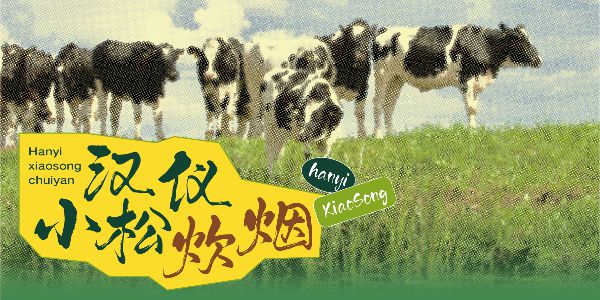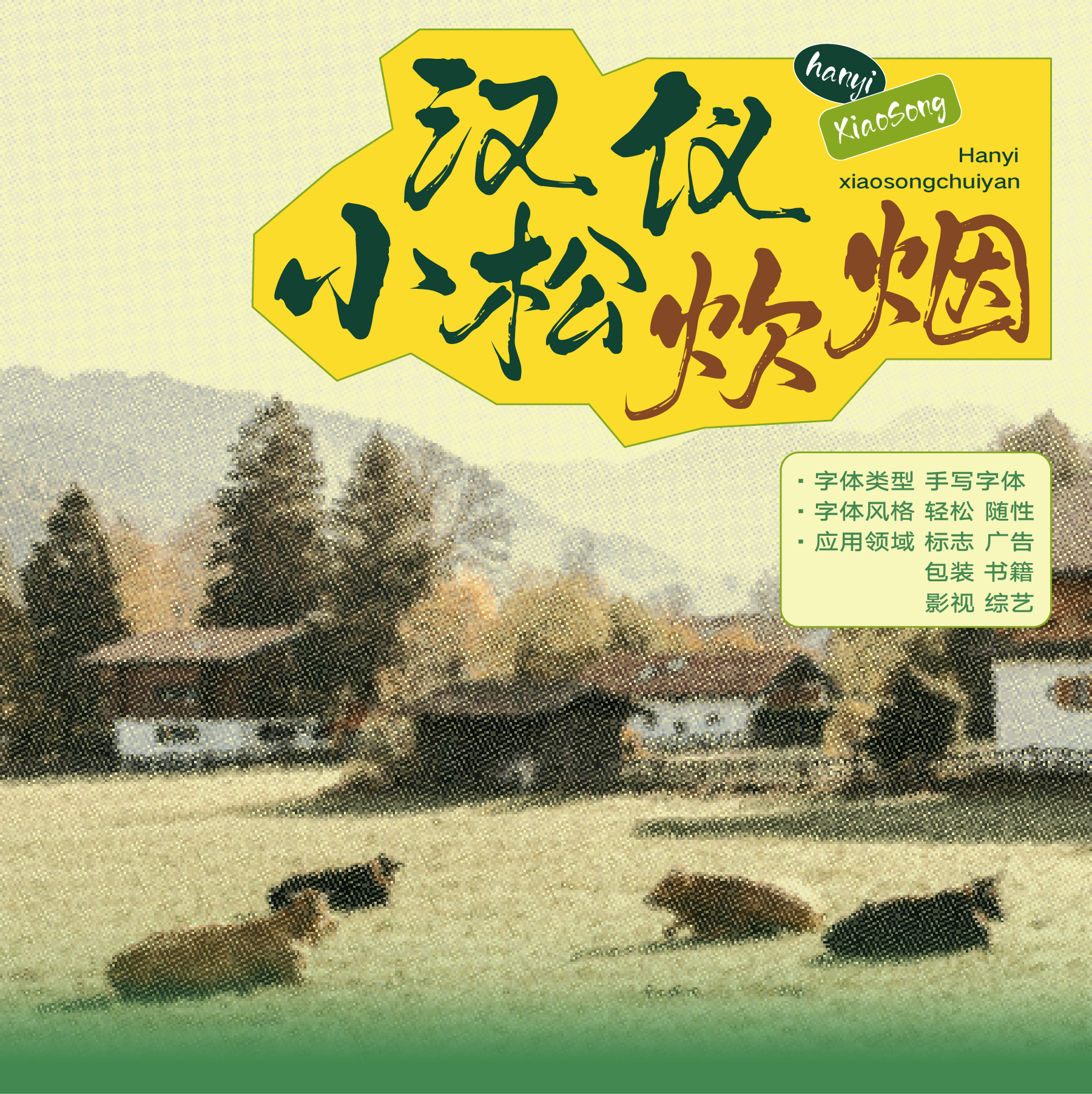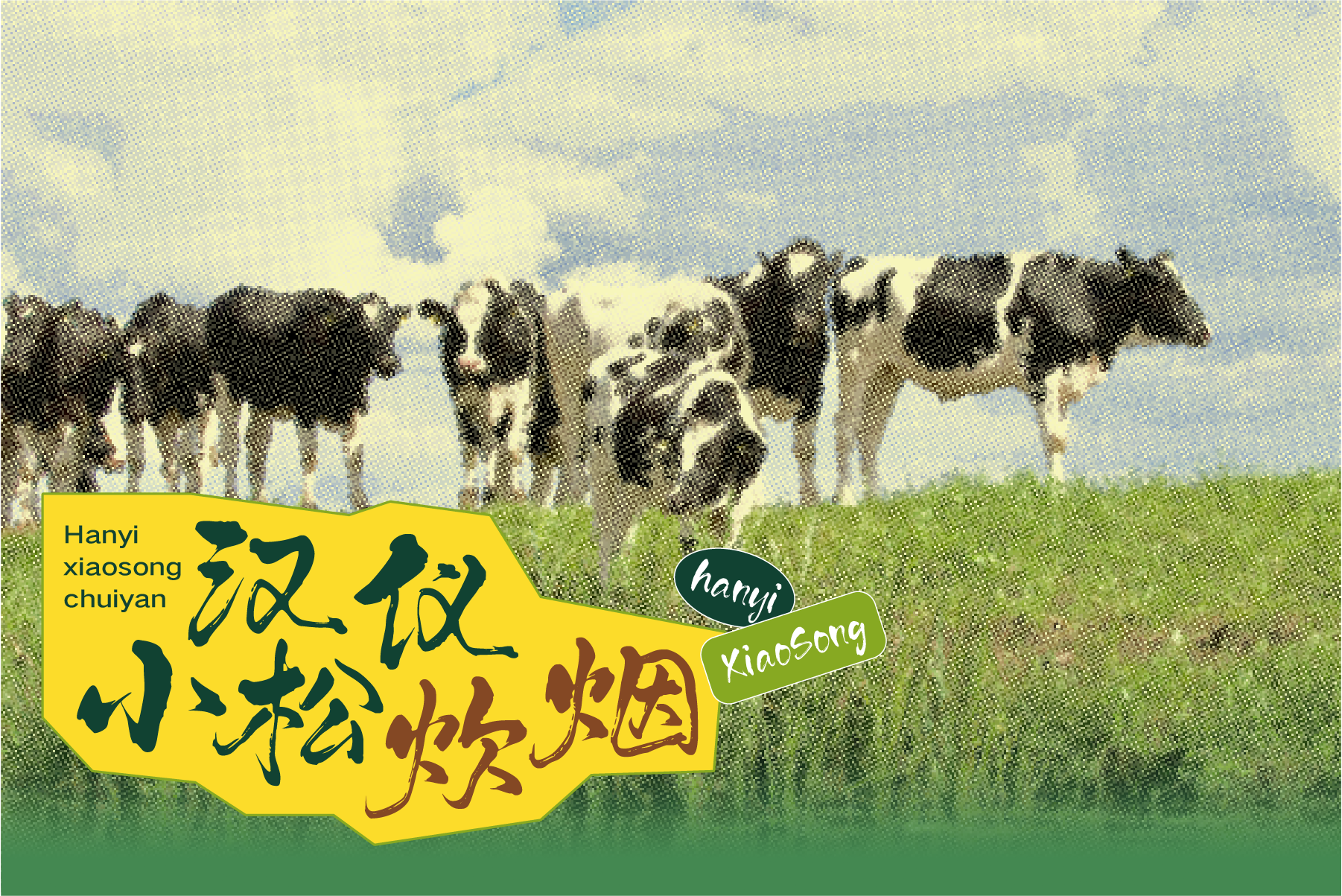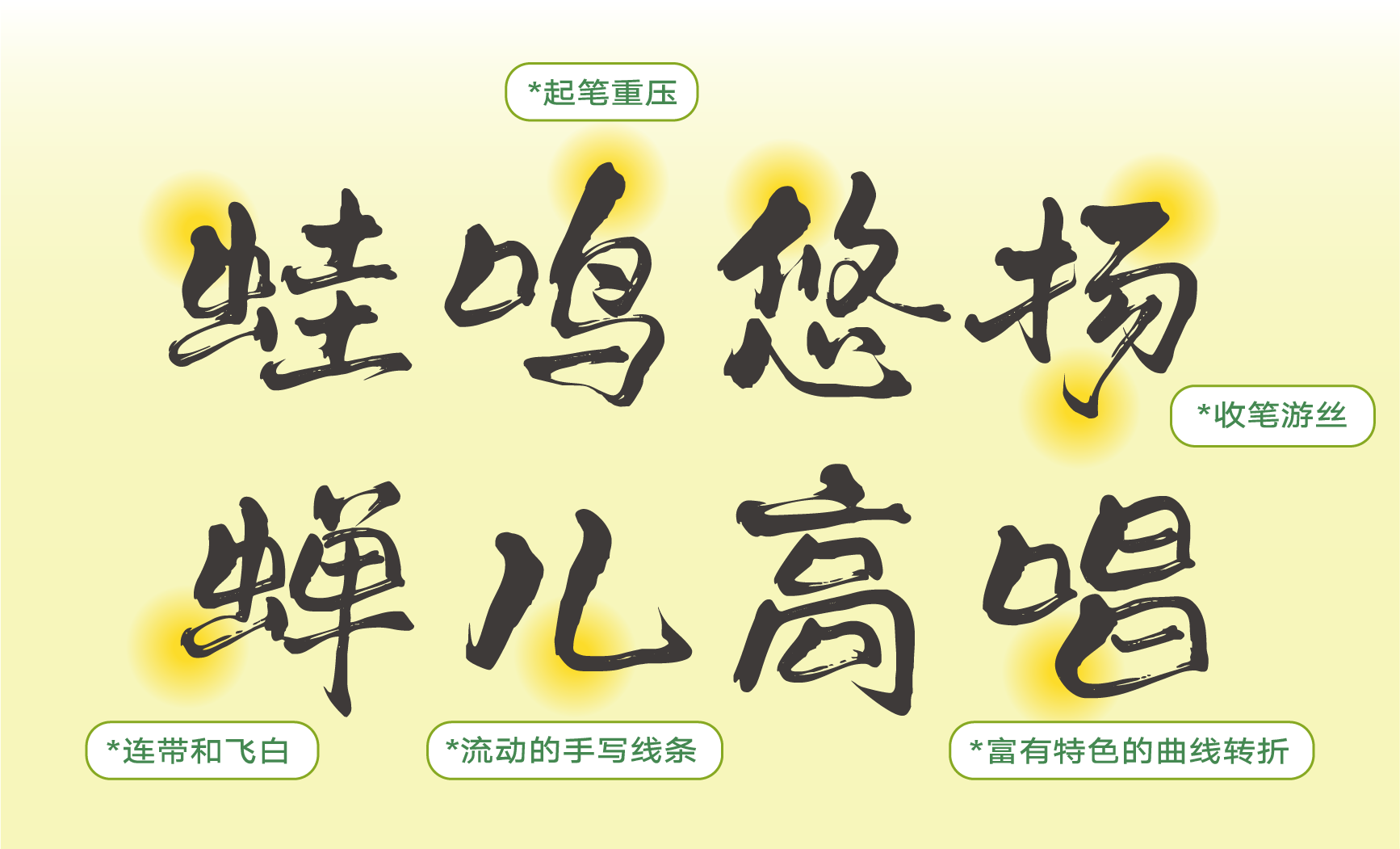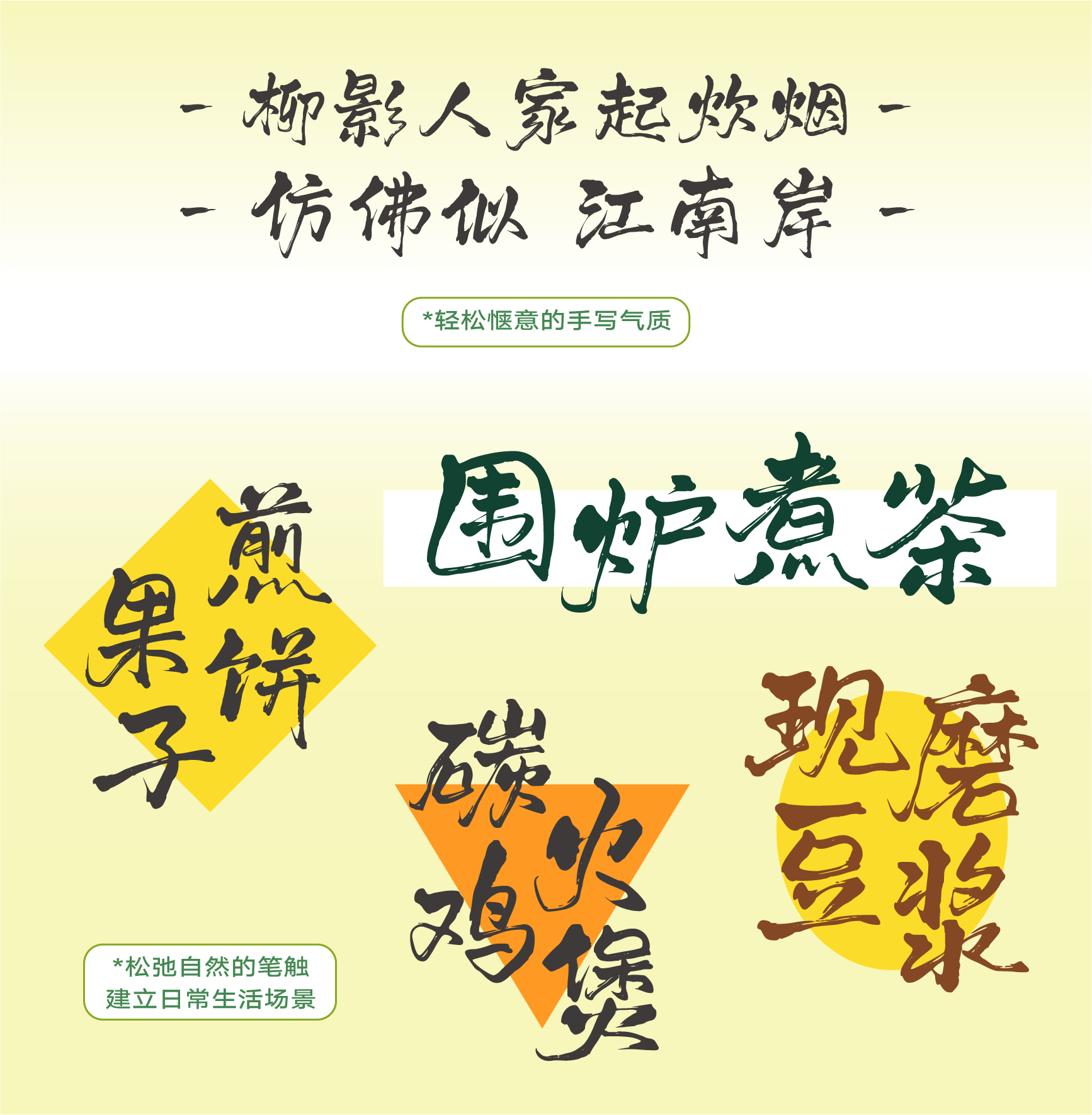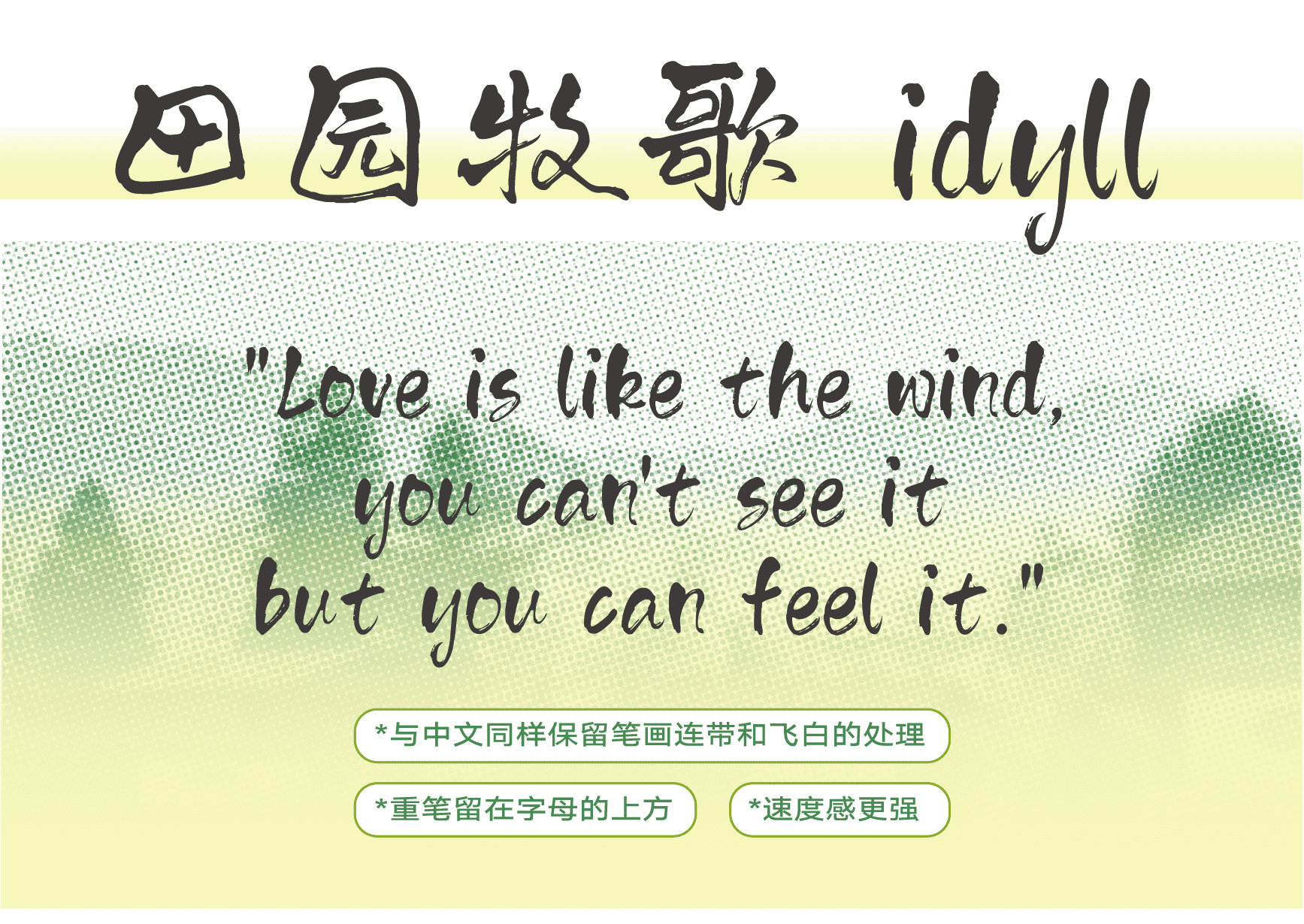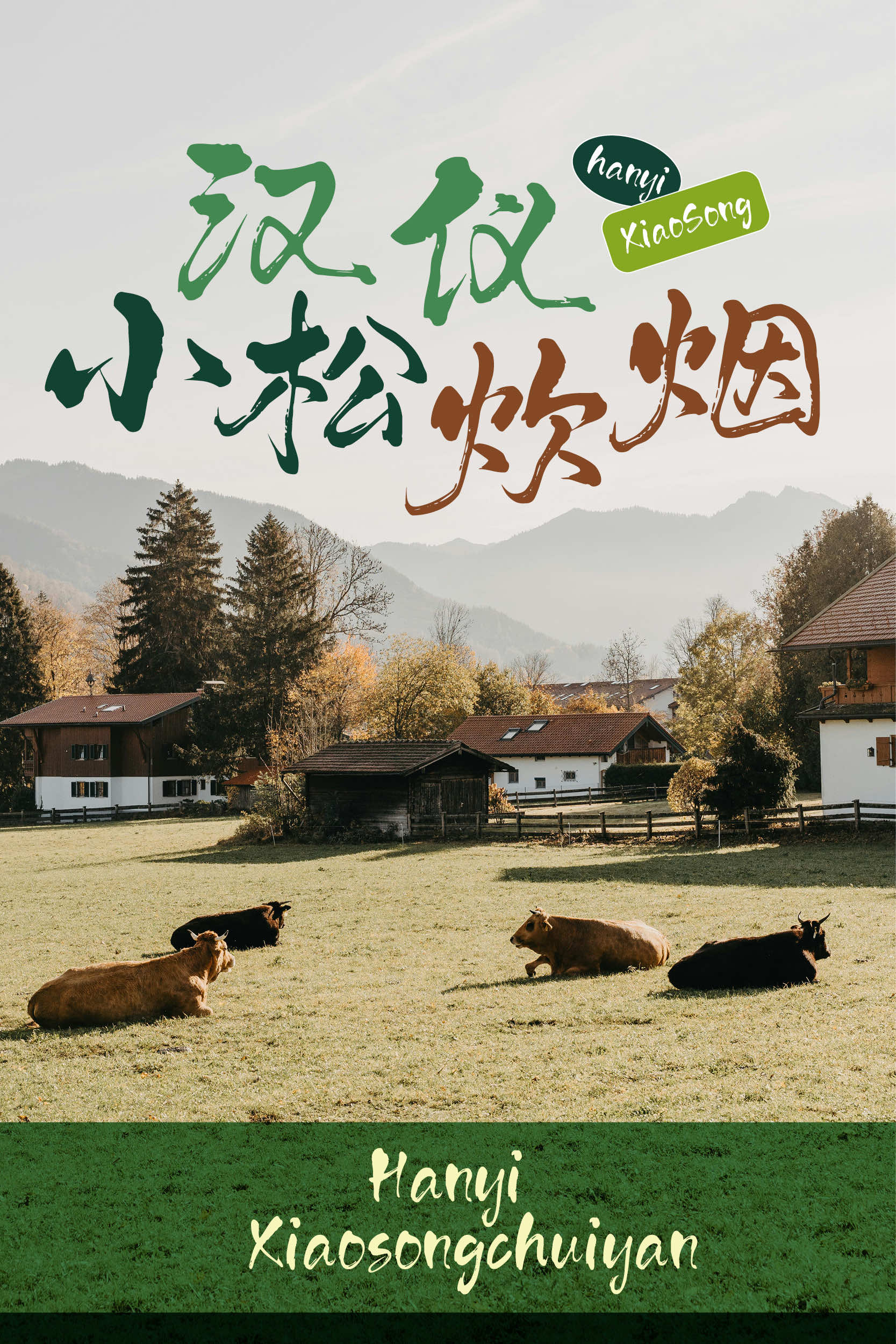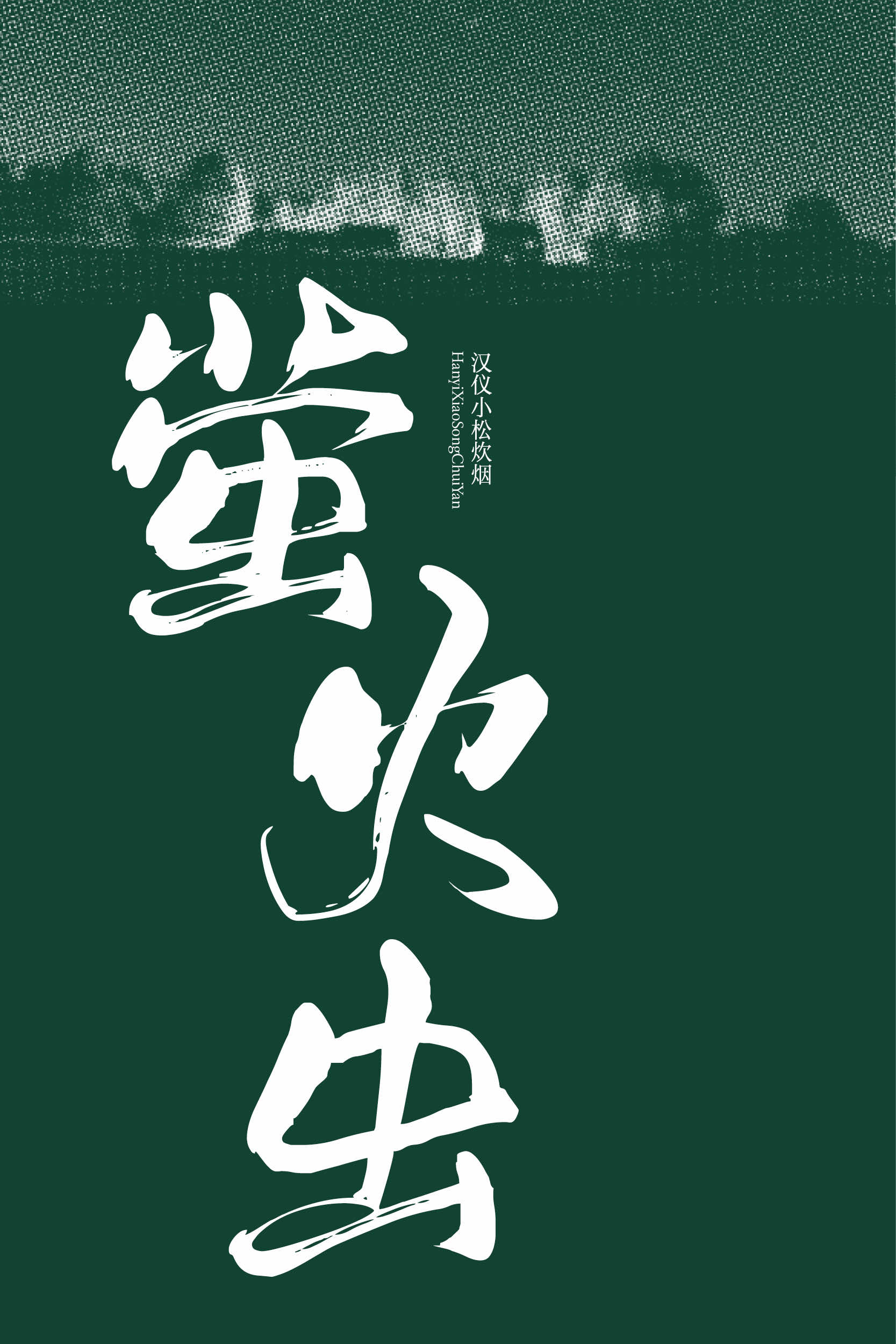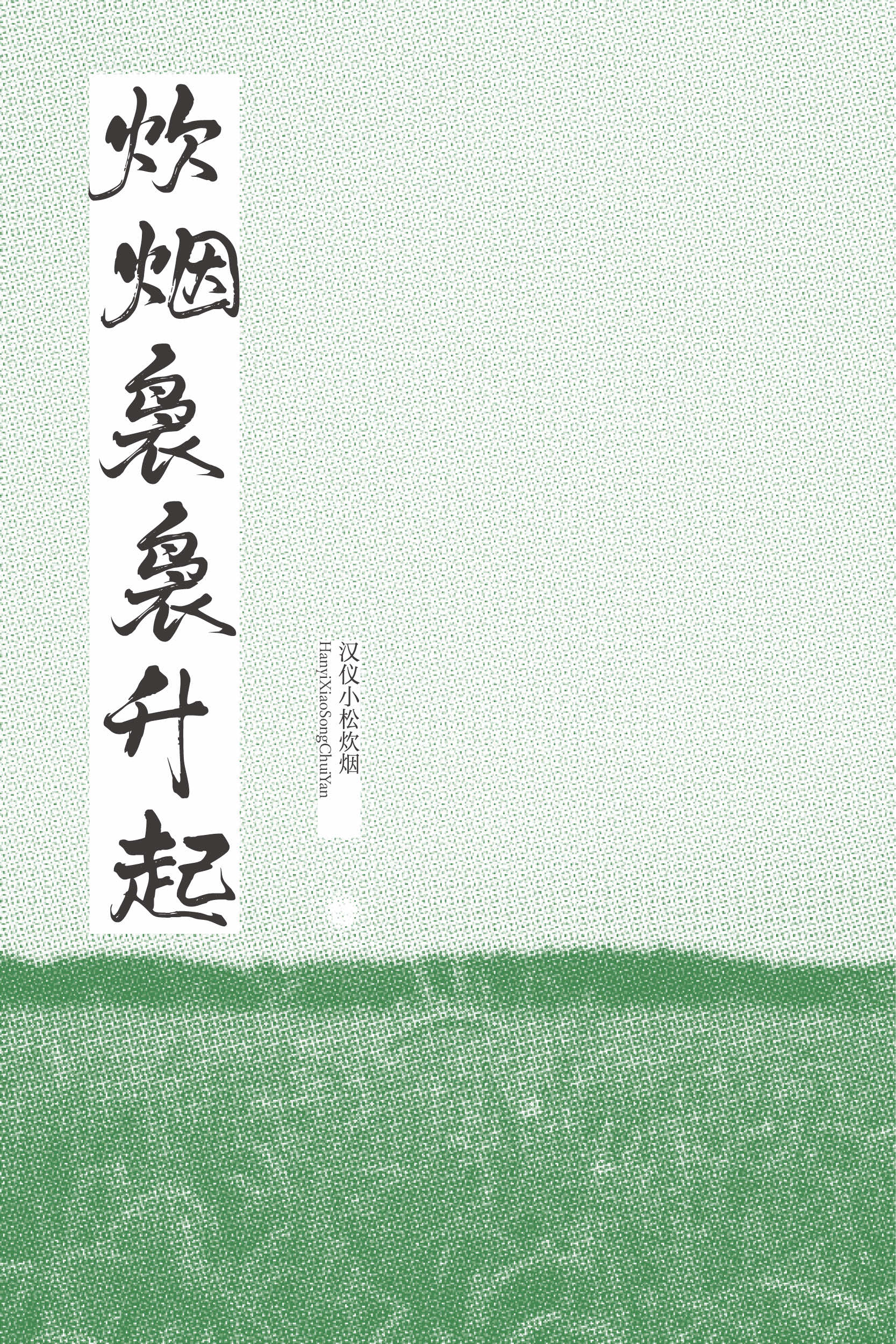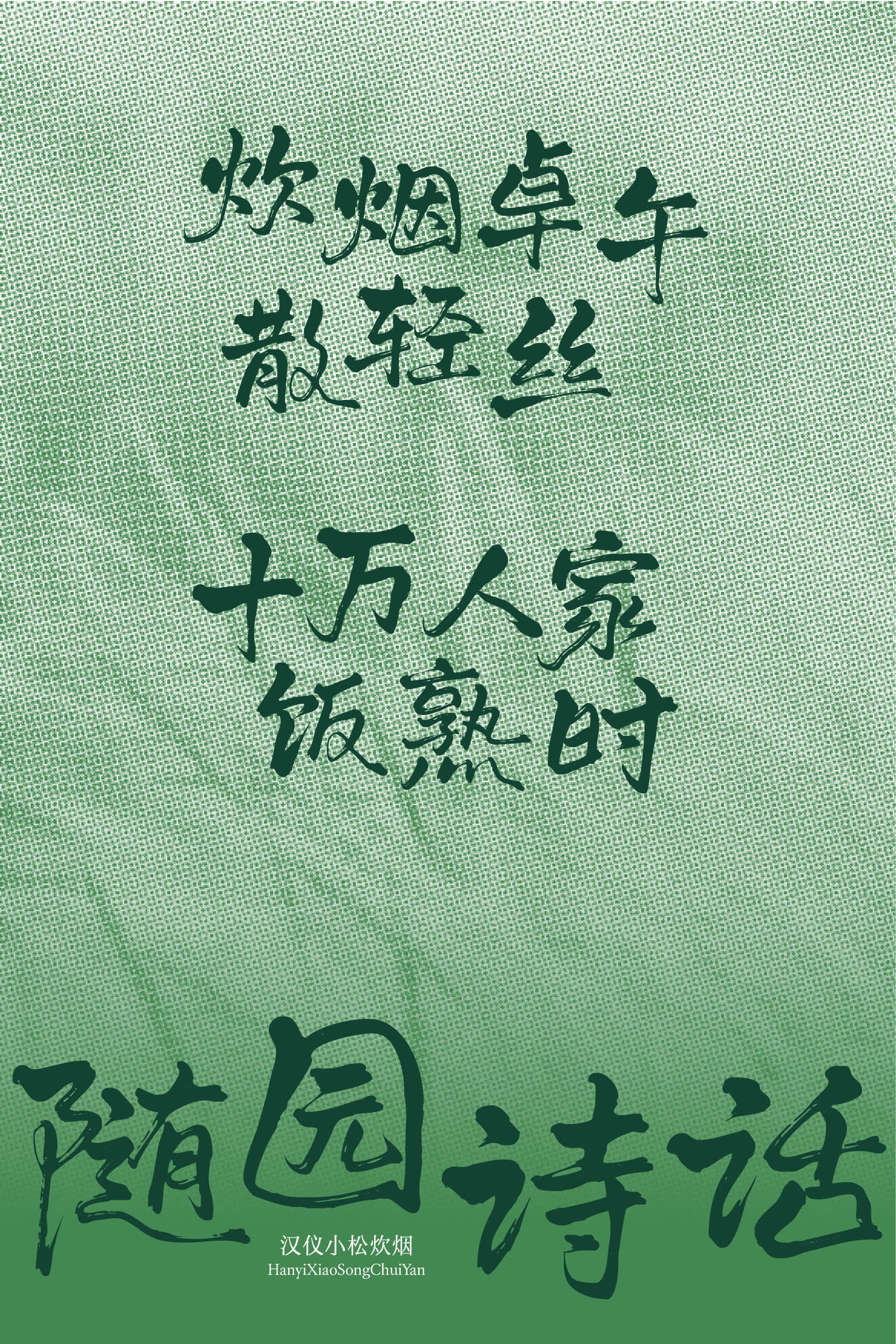
这款字体有自由流动的松弛感
汉仪小松炊烟,意境空灵,仿佛置身于清晨时分的山林之间,远处炊烟袅袅升起,消散在日出之前灰蒙蒙的空气中……以松弛而自然的笔法书写,笔画飘逸如烟雾缭绕,起笔重压,收笔游丝,保留笔画的连带与飞白,线条婉转流动,给人以闲适自得的视觉体验。熟悉亲切的手写感,将人们在繁忙的都市生活里重新拉回到生活中的点滴烟火。在生活化的品牌包装、书籍绘本、影视综艺等使用场景中,营造初生机盎然的朴素与灵巧。
汉仪小松炊烟,以松弛而自然的笔法书写,字面大小不一有节奏变化,整体气质飘逸灵动。
笔画飘逸如烟雾缭绕,起笔重压,收笔游丝,笔画间保留连带与飞白,线条婉转流动,自然、飘渺,怡然自得。
熟悉亲切的手写感,将人们在繁忙的都市生活里重新拉回到生活中的点滴烟火。在生活化的品牌包装、书籍绘本、影视综艺等使用场景中,营造初生机盎然的朴素与灵巧。
汉仪小松炊烟的西文部分与中文匹配,保持上重下轻的设计,书写速度较快,流动感更强,更显轻松随性的风格。